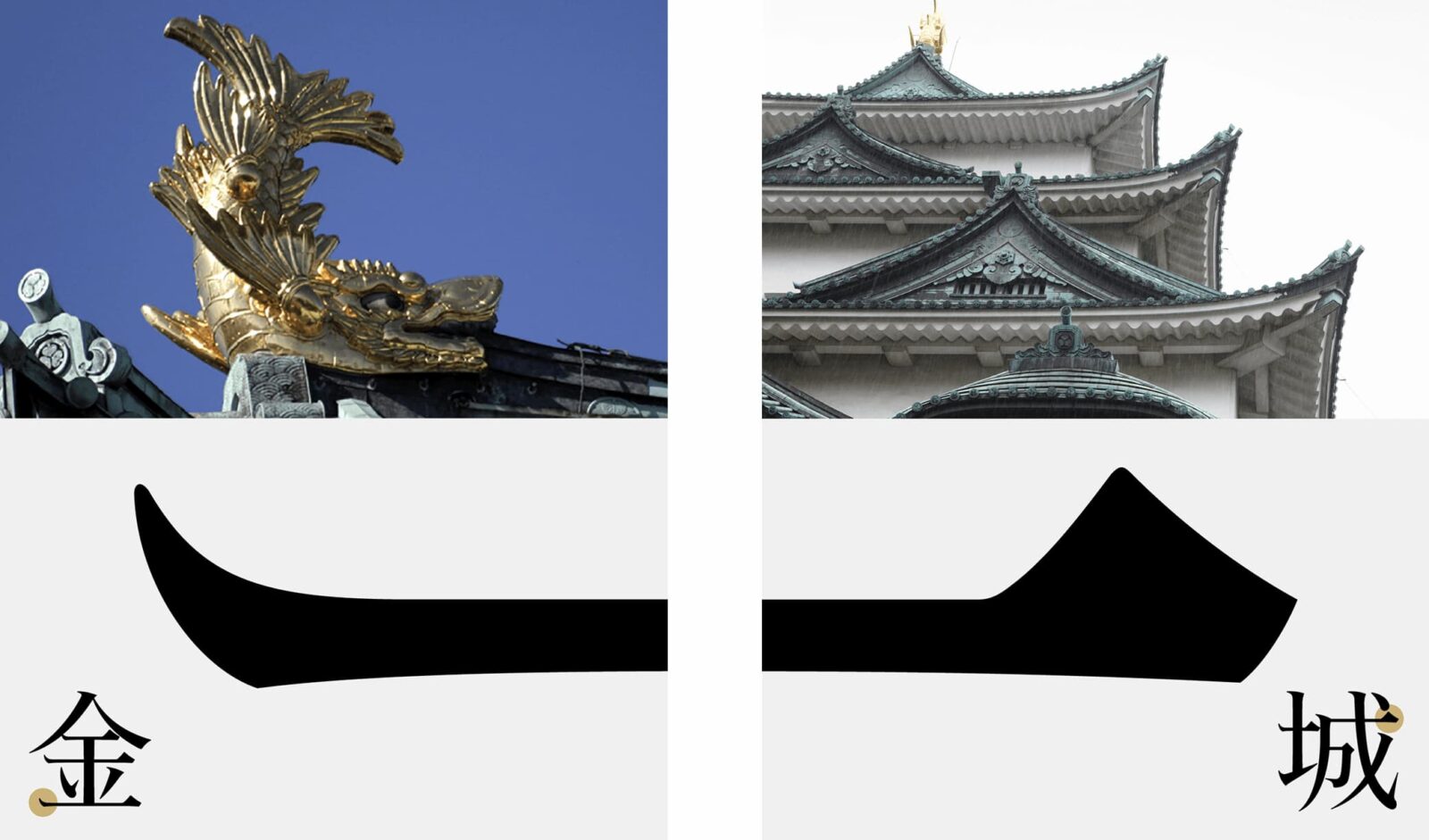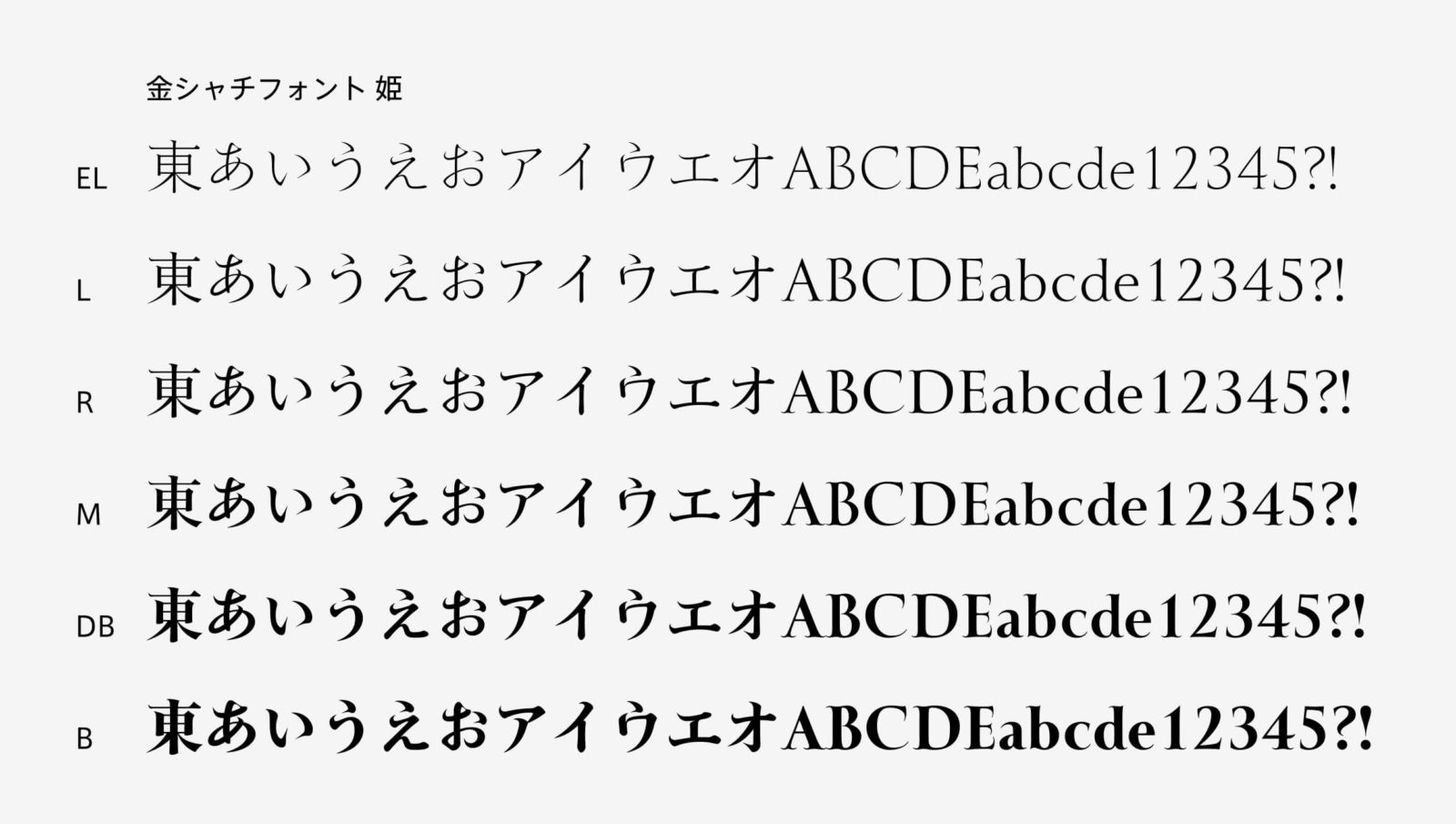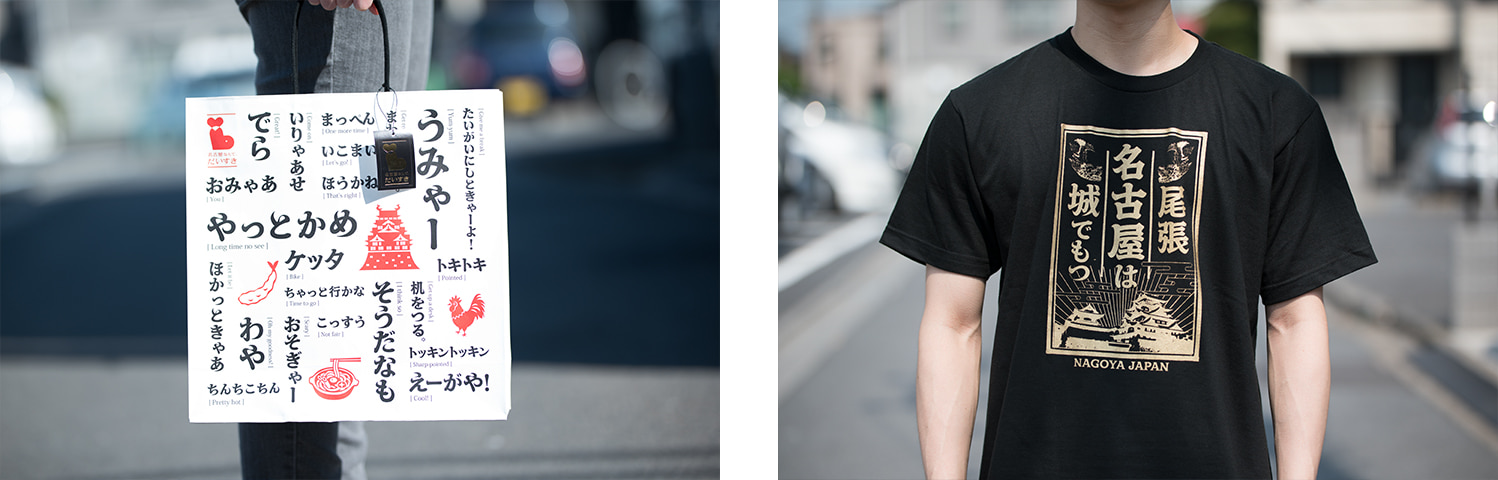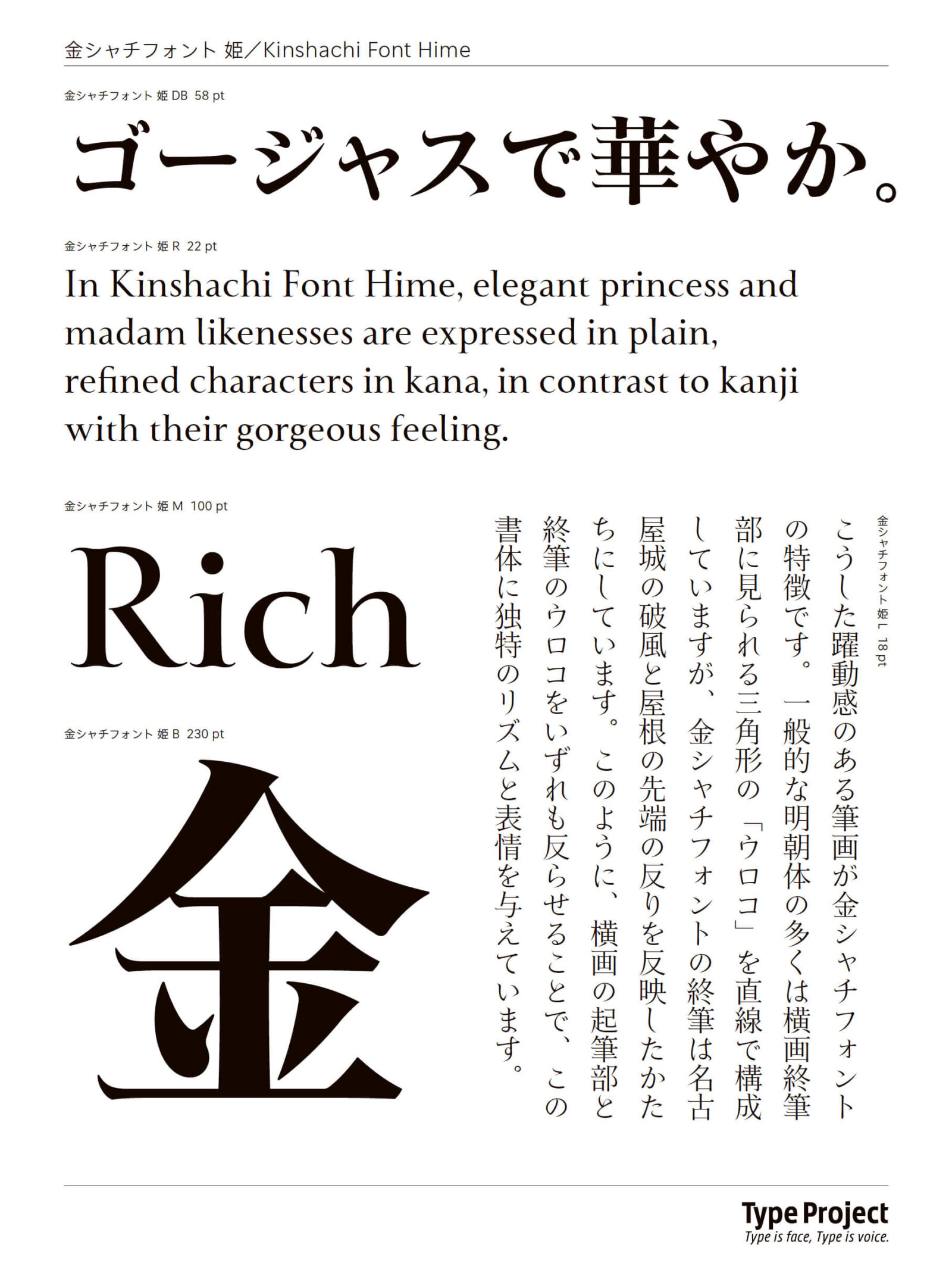
タイププロジェクト、都市フォント「金シャチフォント 姫」の発売を開始
名古屋の文化を書体デザインに反映した装飾的な明朝体
「金シャチフォント 姫」は、漢字・仮名・欧文のそれぞれの独自性を活かしつつ、書体全体としての調和を図った新鮮かつ挑戦的で、華やかなフォントです。個性的で豪華な飾りの要素を取り入れた漢字と、平安時代のたおやかな女手*を手本にした古典的な香りのする仮名、巻き髪のような装飾的なデザインの欧文からなり、日本語の視覚表現にこれまでにないきらびやかな彩りをもたらします。(*女手の呼び名は、平安時代に漢字の使用が制限されていた女性たちが、歌や日記などで平仮名を使っていたことに由来していると言われています。)
タイププロジェクトの代表取締役 鈴木 功は、「地域特有の文化資源を書体デザインに活用する。これは都市フォント構想を貫く基本的な考えかたです。金シャチフォントは、起筆にシャチホコの反り、漢字のウロコに城の破風の形状を反映させるなど、名古屋文化の象徴を取り入れています。名古屋開府400年にあたる2010年に金シャチフォントのプロトタイプを発表し、フォント製品をリリースするまでの10年間に、名古屋の企業や自治体、多くのデザイナーの求めに応じて必要な文字を提供してきました。今後は、名古屋を始めとしてより多くの皆様に、この華やかなフォントを使っていただくことを楽しみにしています。」と述べています。
「金シャチフォント 姫」のファミリーは、EL(エクストラライト)、L(ライト)、R(レギュラー)、M(ミディアム)、DB(デミボールド)、B(ボールド)の6つのウエイトで構成されています。
金シャチフォント 姫
■ 使用例
金シャチフォントを採用した、パックタケヤマ社のジャパン手提げ袋 名古屋弁バージョン、大須おみやげ カンパニーの名古屋T シャツなどが販売されています。